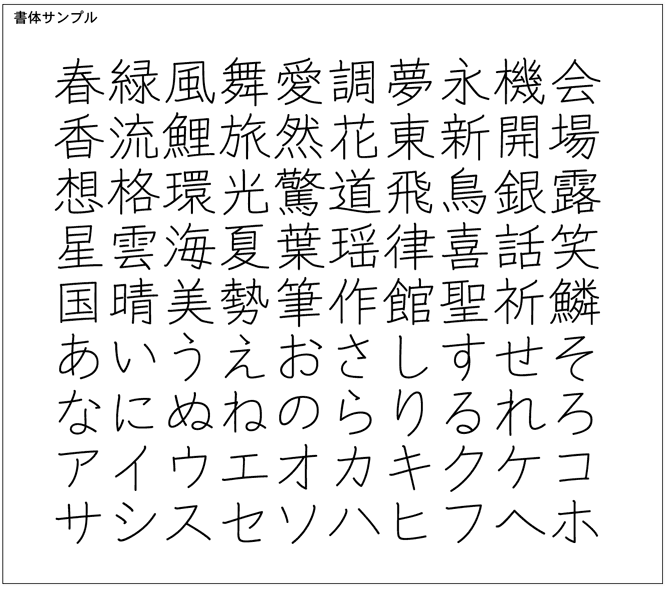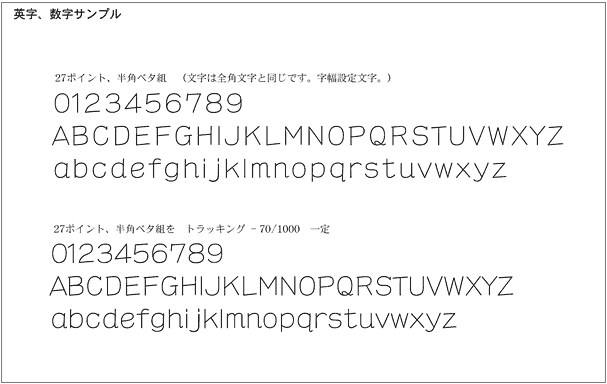
ナカライン - L
Open Typeフォント [ ナカライン - L ] を発売しました。
この書体は、楷書体系で丸線によってフリーハンドでデザインしたオリジナル書体です。
明朝体や角ゴシック体とは異なった、自由で伸びやかな感覚の文字を目指しました。ユーザーの皆さまに広くご使用いただければと念願いたします。